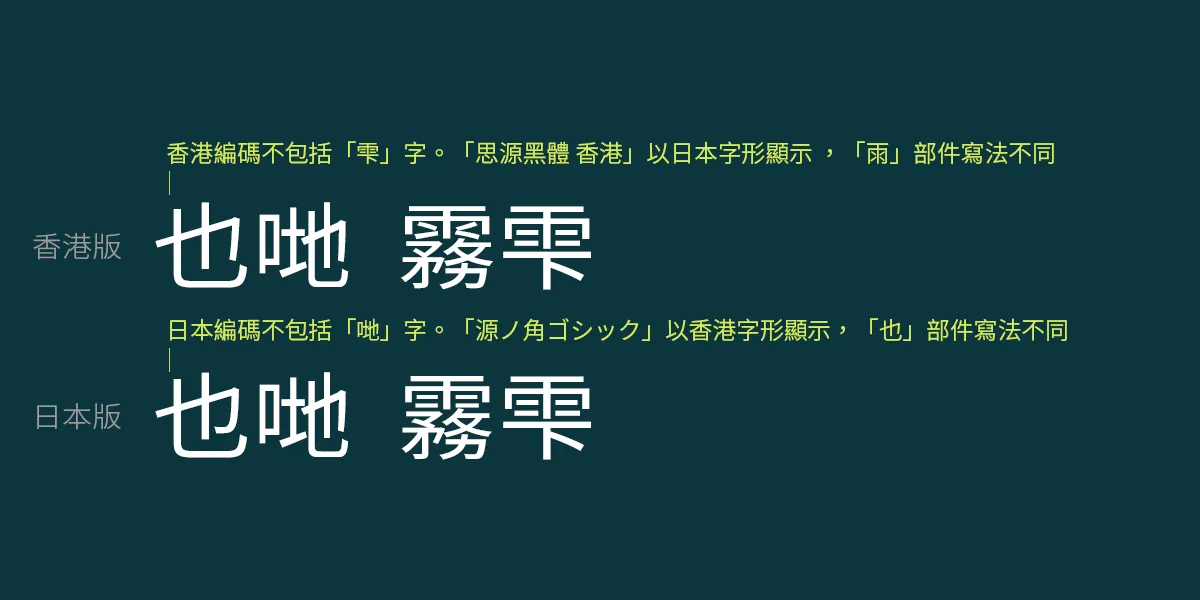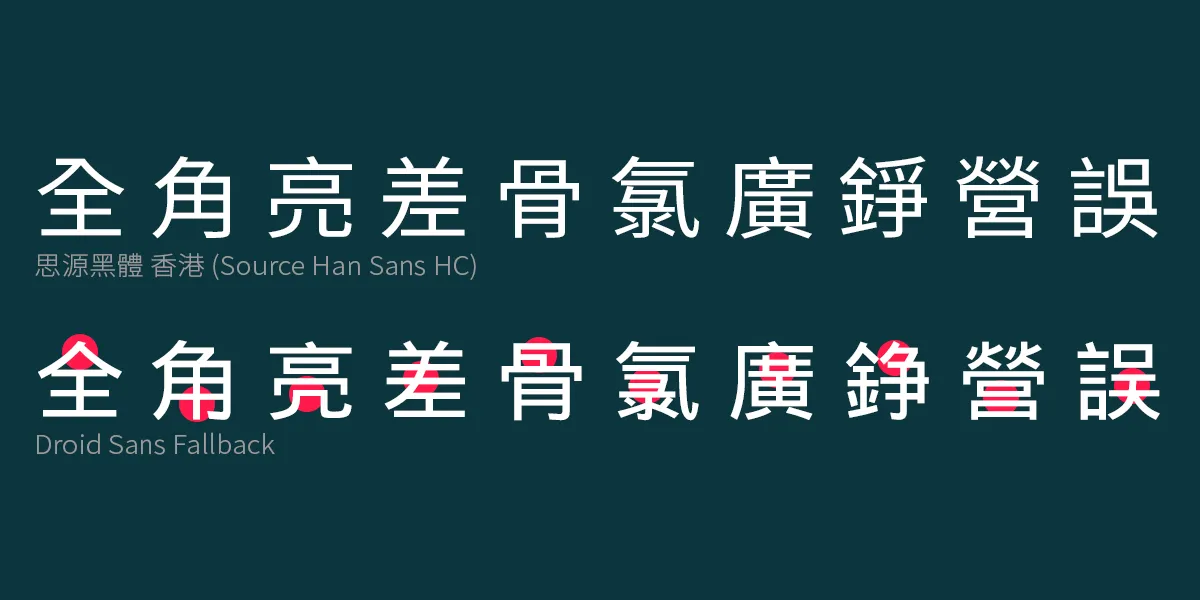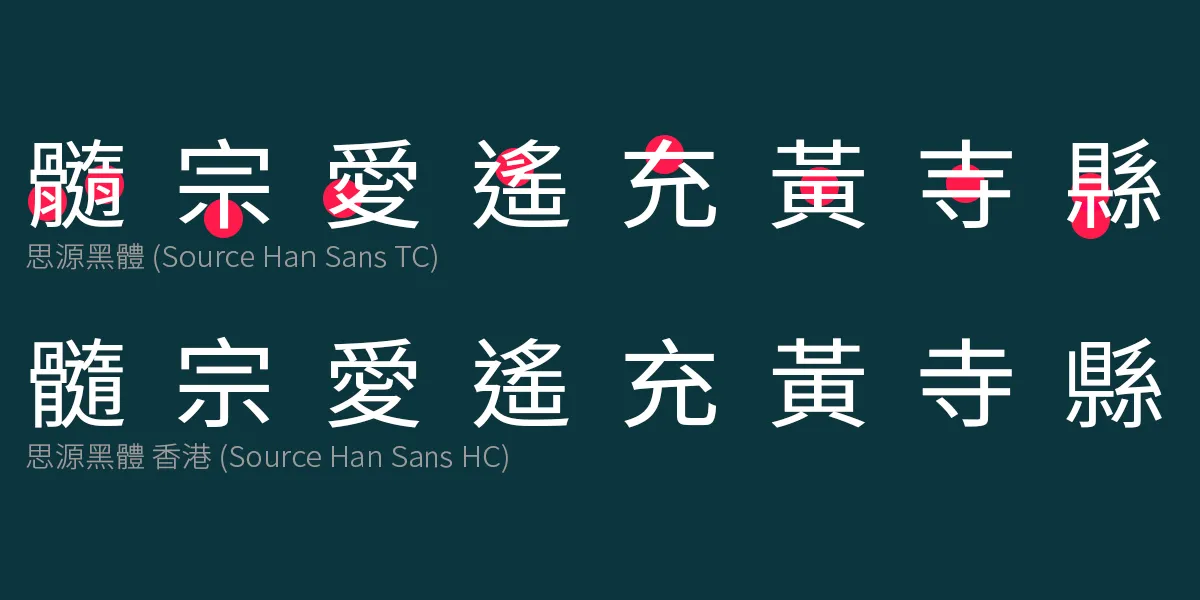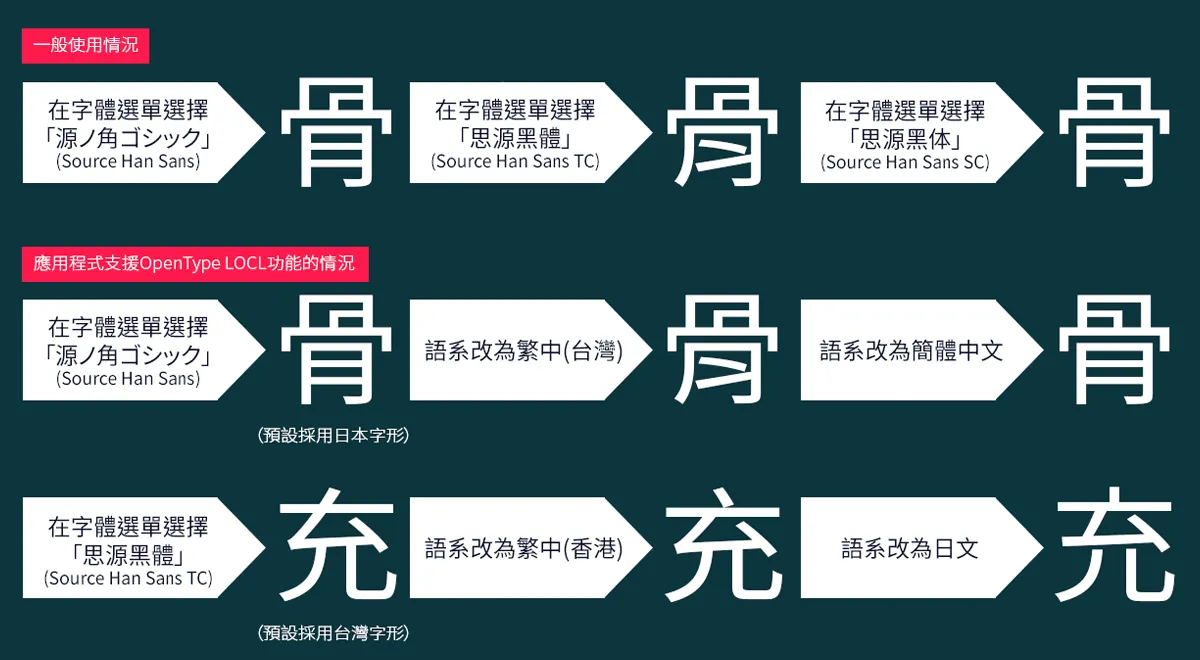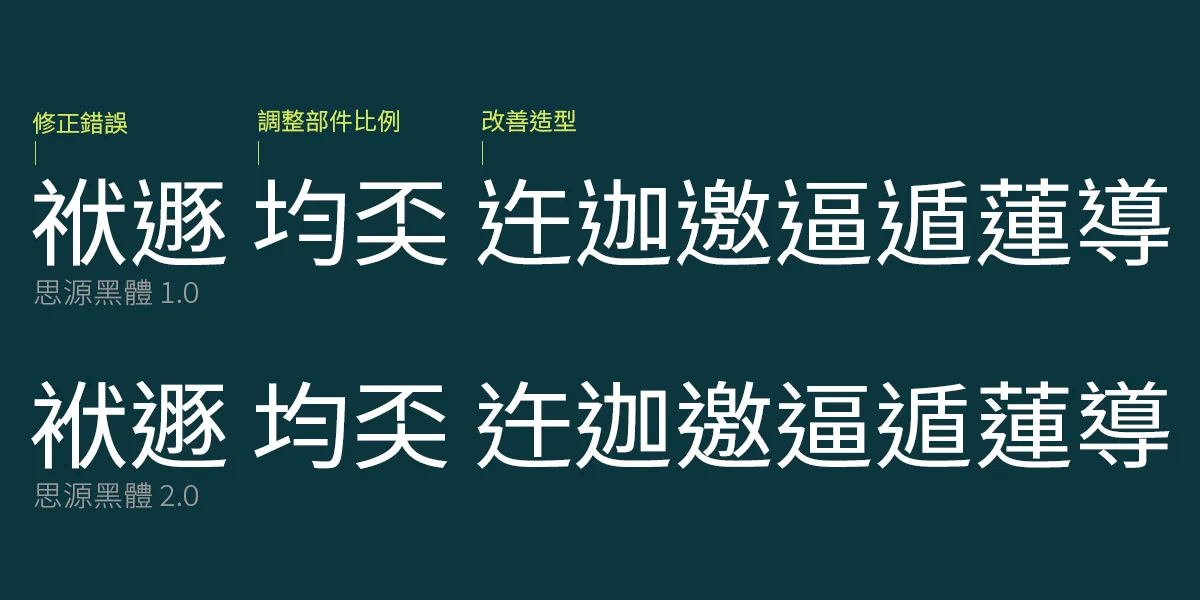
思源黑體 2.0 介紹
2014 年 7 月,思源黑體正式發表。這款字體不特收字多、提供七種粗幼,更支援繁體(正體)中文、簡體中文、日文、韓文四個語系的書寫系統,加上完全免費、授權自由,一推出便瞬即吸引漢字文化圈大眾目光,並獲得廣泛報道。雖然這款字體的繁體中文版本是根據台灣教育部「國字標準字體」(簡稱台標)所制定的筆形製作,當中的字形未必符合香港慣用寫法,大眾仍樂於使用,現在這款字體在香港可謂隨處可見。
事隔四年,思源黑體在 2018 年 11 月迎來第一次重大更新,推出 2.000 版。更新重點之一是將本來的繁體中文版拆分成「台灣」和「香港」兩個版本,香港版字型名為「Source Han Sans HC/思源黑體 香港」,當中的字形是遵照香港標準製作(Source Han Sans TC/思源黑體仍是台標版,名稱不變)。這個版本對香港使用者來説其實甚具意義,只是可能因為新版在技術上不如初版般震撼,對其他地區用戶影響又不大,以致相關報道不多。所以趁着思源黑體 2.001 版更新推出不久,寫下這篇文章,介紹一下這個新版的思源黑體。
1. 温故知新:「思源黑體」簡介
思源黑體是 Adobe 和 Google 兩家公司合作開發的泛中日韓字型產品。Adobe 本身有以 “Source” 為名的英文開源字體,如 “Source Sans Pro”、“Source Serif Pro” 之類;Google 也有一系列以 “Noto” 為名的多語系開源字體,例如英文的 “Noto Sans”、希伯來文的 ”Noto Serif Hebrew” 等等(大多由 Monotype 蒙納製作)。到了中日韓字體,Google 選擇與 Adobe 合作,共同開發,再將成品各自以自己的品牌推出,以配合他們本身的開源字體家族產品線。
Google 的版本以 Noto Sans CJK 為家族名稱,並以語系代碼為符合各地寫法的字型命名。例如台灣繁體中文版字型名為 Noto Sans CJK TC(TC 本來是繁體中文,沒有地區之分,採用台灣寫法,但為保持兼容性應該不會修改)、新增的香港版名為 Noto Sans CJK HK、日本版名為 Noto Sans CJK JP。
Adobe 則將這款字體家族命名為 Source Han Sans,這個也是日文版字型名稱。其他地區的字型,家族名稱後面會有語系代碼:繁體中文是 TC,新增的香港是 HC,簡體中文是 SC,韓文是 K。除此之外,Adobe 還為這款字體所支援的語系改了一個本地化名稱:繁體中文叫「思源黑體」、簡體中文叫「思源黑体」、日文叫「源ノ角ゴシック」、韓文叫「본고딕」。這些本地化家族名稱同時是相關語系的字型在字型選單顯示中會用到的本地化名稱,所以台灣繁中版的字型名稱是既是「Source Han Sans TC」亦是「思源黑體」、簡中版既是「Source Han Sans SC」也叫「思源黑体」。香港和台灣都用繁體中文,為免撞名,香港版的中文名稱作「思源黑體 香港」。選單中顯示的是英文抑或本地化名稱由作業系統或應用程式決定。
雖然「思源黑體」既可以是這款字體的家族名稱、也可以是實際安裝後的台灣繁體中文版字型檔,但一般使用上應該不會混淆。總之,「思源黑體」是 Adobe 發表時所用的字體家族中文名稱,跟 Source Han Sans 和 Noto Sans CJK 是同一回事。
思源黑體(或 Google 的 Noto 字體計劃)最終目標是完整覆蓋 Unicode 字集的表意文字字符。雖然還未能做到,但現時這款字體所支援的字元應能滿足一般人的需要。
在電腦存取中日韓字元有一難題:即使是同一個字、在 Unicode 獲分配同一個碼位,各地的標準字形可能會有差異,這就是所謂的「地區變體」。一般的中文字體通常只會提供一種寫法(可能是根據某一地區標準設計,也可能不是),思源黑體的最大特點是透過 OpenType 技術中的 LOCL 功能,讓使用者可以在單一字型中選擇符合不同地區標準的字形式樣。不過,這種方法必須經由軟件支援,而目前支援這功能的軟件並不多,這就是思源黑體仍然有提供「分區版」字型的原因。(話説最初思源黑體推出時,官方只有一款「Source Han Sans」字型檔,其本意是使用者在程式中選擇這款字型、再透過語系切換去獲得該地區的本地化寫法,沒有選擇地區則預設輸出日本版字形。這解釋了為何日本版思源黑體就直接叫做 Source Han Sans 而沒有語系代碼。但由於支援這種做法的軟件有限,反而對使用者造成不便,所以製作方在其後版本才加入以各地區寫法為預設字形的「分區版」。分區版只是預設字形有變,使用者仍可以用 LOCL 功能切換至其他地區字形。)
OpenType LOCL 應用示例
2. 有關「香港標準」字形的説明
「思源黑體 香港」的筆畫依據是香港政府新近發表的《香港電腦漢字參考字形》。
香港標準字形的制訂,最早可以數到教育署語文教育學院(今香港教育大學)在 1989 年出版的《常用字字形表》。這本書為 4,700 多個常用字訂定標準字形,主要供小學教師、學生、教材出版者參考,藉此減低語文教學時因異體字太多對師生所造成的困擾。
常用字字形表書頁
原版和直至 2000 年為止的修訂本,書中的標準字形都是用人手以楷書寫成,就是上圖的樣子。到了 2007 年才改用電腦楷書字體修訂重排,附於教育局出版的《香港小學學習字詞表》內(也有網頁版)。
《常用字字形表》本來是為手寫楷書而設。2002 年,政府推出根據這本字表製作的《香港電腦漢字字形參考指引》,首次提供楷體和印刷體(文件的參考字樣為宋體)的電腦字形供業界參考(印刷體是指專為印刷而設的字體,如宋體、黑體之類;電腦上的楷書字型仍算手寫體)。2017 年 5 月,當局再發表《香港電腦漢字參考字形》,簡單來説可以看成是之前《指引》文件的更新修訂本。
當然,每個人的書寫習慣都有不同,《參考字形》出來的結果未必人人都會滿意。但大體上,根據《參考字形》製作的字體的確會比根據台灣「國字標準字體」製作的字體較適用於香港。試比較以下各字:
香港、台灣標準字形差異舉隅
思源黑體香港版的意義在於:符合香港慣用寫法的電腦字型長期以來都被作業系統廠商忽視,而「思源黑體 香港」有望可以改變這個情況。
大家在街上看到和用在報章雜誌上的不盡是台灣或香港標準字形,因為印刷字體也有很多種面貌,例如傳統印刷體。至於香港或台灣的商業字體,設計師也會因應某些筆畫用在印刷體是否合宜而作出調整,不會完全遵照港標或台標的寫法(近年由於思源黑體的出現,使用台標字體的情況有所增加)。不過,在電腦或手機熒幕又是另一番風景。
專為電腦顯示而制訂的《香港電腦漢字字形參考指引》在 2002 年公佈,台灣的類近標準是 1993 年的《國字標準字體宋體母稿》。兩項標準均屬自願性質,並不強制電腦或字體廠商遵從。
在 Windows 系統,細明體一直是正體中文環境的介面字型,本來使用傳統印刷體字形,大約在 2005 年更新後改為依照台灣「宋體母稿」筆形設計,也就是「思源黑體」台灣版的款式,沒有提供香港筆形版本。2007 年新發表、正體中文環境使用的介面字型「微軟正黑體」依然只有台標版。結果是,台標字形成為 Windows 系統的事實標準,香港用家使用 Windows 系統,預設看到、用到的也只會是台標字形(順帶一提,九巴有不少站頭的大型乘車指示牌也是使用微軟正黑體)。
另一方面,中國大陸有法律規定電腦產品中的中文字體無論繁簡都必須符合當局指定的字形,屬強制標準(大陸的編碼標準包攬繁簡體,但字形跟港台未必相同)。由於港台無此規定,基於成本考慮,一些廠商在港台上市的電子產品便未必會再額外花錢在符合港台寫法的字體上,而是直接選用大陸字體,港台用家無可避免會被牽着鼻子走。有錢如 Google,它的手提電話作業系統 Android 最初亦只有一款使用大陸標準筆形的中文字體 Droid Sans Fallback,到了 2014 年底才加入使用台灣筆形的思源黑體繁體中文版。
Droid Sans Fallback 字型
在資訊處理世界,香港的字體使用實際上是處於「台標」與「陸標」之間的夾縫中。
雖然「思源黑體 香港」不是第一款按照香港筆形製作的黑體字型產品(Apple 在 2015 年推出的「蘋方」就有支援香港和台灣兩地標準),但它卻是第一款按照最新《香港電腦漢字參考字形》標準製作的免費開源黑體字型,也相信會成為將來 Android 系統設為香港地區時使用的預設字體。
思源黑體支援港五地的特定字符集,並會在各地字符集範圍內提供符合當地標準的字形。所以,思源黑體在字碼上的覆蓋範圍是這款字體所支援字符集的總和。而思源黑體香港版支援 Big5(大五碼)及 HKSCS-2016(香港增補字符集-2016)字集共一萬七千多字,意思是這些字的字形都會根據《香港電腦漢字字形參考指引》製作(不過由於思源黑體的泛中日韓特性,一些各地字形上的細微差異可能會被忽略,以使字圖得以共用)。
以收字量來説,思源黑體的發佈格式可以分為「完整版」和「子集(Subset)版」兩個版本。其中 Subset 版只包含該語系覆蓋範圍內的字符,例如「思源黑體香港子集版」只會收錄 Big5 加 HKSCS-2016 字集的一萬七千多字,也不支援之前提到的 OpenType LOCL 特性。「完整版」的「思源黑體香港」則包含所有中日韓字符集的字符共三萬多字(連同地區變體)。只是假如一個字不在香港字符集範圍,出來的字形未必一定符合「港標」寫法而已。
思源字體各地的支援字碼範圍並不相同
思源黑體不但名稱多,發佈的格式也頗多,使用者可能會感到疑惑,這裏稍做説明。
思源黑體發佈格式概覽
四種格式中,首先不建議使用 Region-specific Subset 版本(即上表最左邊那一個),原因是收字量較少,使用這版本遇到缺字的機會相對較大。
Language specific OTF 和 OTC、Super OTC 的收字量和字型數量完全相同,只是封裝格式有別:OTF 版一個檔案收錄單一地區的一個字重,OTC 版將 OTF 各地區版本中同一字重的字型集合成單一檔案,一個檔案內就有相同字重的不同語系版本。Super OTC 更是「攞你命三千」,進一步將 5 個地區、7 款字重共 30 多個字型集合成單一檔案。這純粹是減少安裝上的麻煩和節省儲存空間(以 OTF 方式安裝所有語系字型佔用超過 500MB 空間,Super OTC 則不過 100MB),也有點技術展示的意味,但使用上並無分別。要留意的是 OTC 算是新格式,需要較新的作業系統才會支援,即使可以安裝,某些軟件使用 OTC 字型時也可能會遇到兼容問題。
換言之,Language specific OTF 格式是目前兼顧收字量與軟件兼容性的最佳選項,使用者也可以根據需要只安裝個別地區的字型。但想一次過安裝多區字型的也可先試試 OTC 或 Super OTC,有問題才轉回 OTF。
思源黑體 2.0 版其他更新
雖然距離思源黑體 2.0 版初發表將近半年,但在香港街上(商場內、交通工具上的廣告)、網上(報章、網站在 Facebook 專頁發佈消息時的預覽圖片)看到的思源黑體還是使用第一版台標的居多。這可能是因為很多人不知道「思源黑體」會像軟件般不時更新。但在增加香港字形之外,思源黑體 2.0 其實還有不少修正和改進,而最新的 2.001 版除了增加日本新年號「令和」的合字全形符號(U+32FF「㋿」),也修正了不少香港版字形問題,值得更新。 希望這篇介紹可以令更多人留意到思源黑體香港版的存在,並嘗試使用。
• 思源黑體香港版根據的《香港電腦漢字參考字形》跟《常用字字形表》的標準字形並不完全相同。例如「甜」字《字形表》首筆作橫,兩年前曾經有過一陣議論;現在《參考字形》採用了首筆作撇的寫法。
• 現在大多數瀏覽器已經支援 OpenType LOCL 特性。假如你在網頁指定使用「思源黑體香港版」,但網頁的語系設定為日本(ja-JP),瀏覽器便會調用思源黑體香港版中的日文字圖顯示。遇到「明明指定了A版地區字型仍然出現B版地區寫法」時,可以看看是否這個特性在作怪。